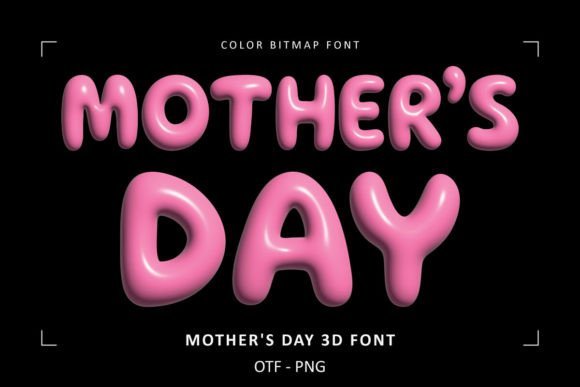
Mothers Day 3d Font
Mothers Day 3D Font – أضف لمسة سحرية لتصاميمك!
احتفل بعيد الأم بأناقة مع Mothers Day 3D Font، خط ثلاثي الأبعاد مصمم خصيصًا لإضفاء طابع دافئ وجذاب على تصاميمك. يتميز هذا الخط بتفاصيله الفريدة وأسلوبه العصري، مما يجعله مثاليًا لاستخدامه في بطاقات التهنئة، التصاميم الإعلانية، منشورات وسائل التواصل الاجتماعي، الهدايا المخصصة، وغيرها الكثير!
???? مميزات الخط:
✔ تصميم ثلاثي الأبعاد أنيق وجذاب
✔ مثالي لبطاقات عيد الأم والتصميمات العاطفية
أطلق العنان لإبداعك وأضف لمسة من الجمال والدفء إلى تصاميمك مع Mothers Day 3D Font! ????✨